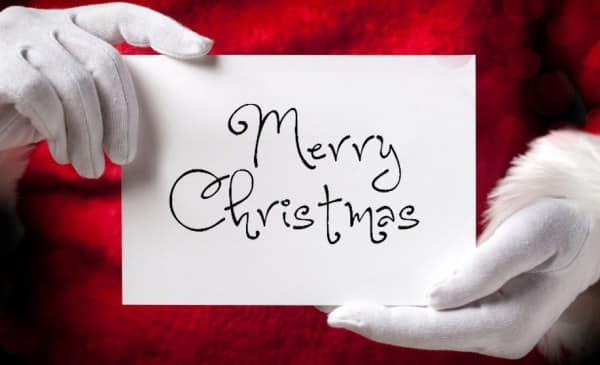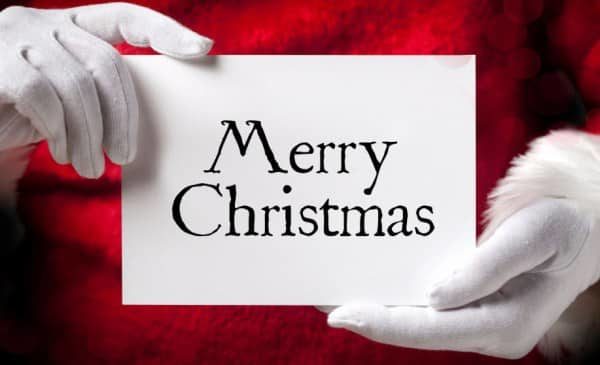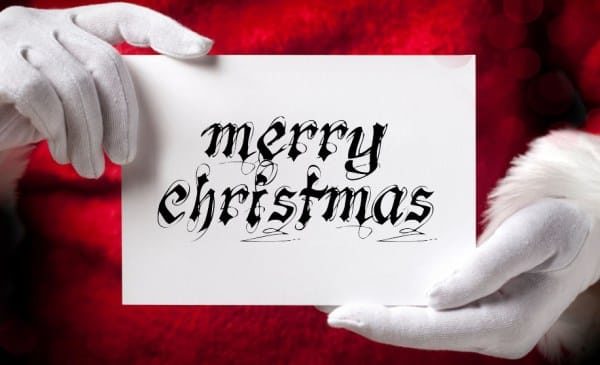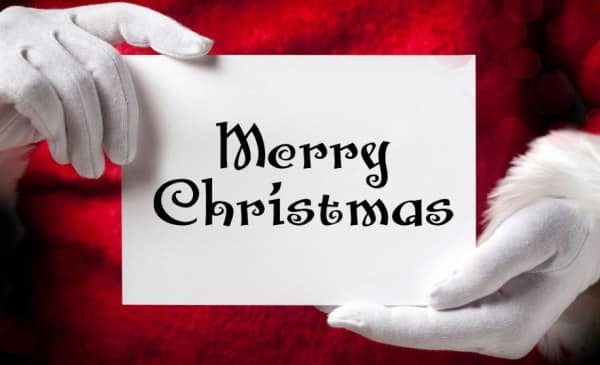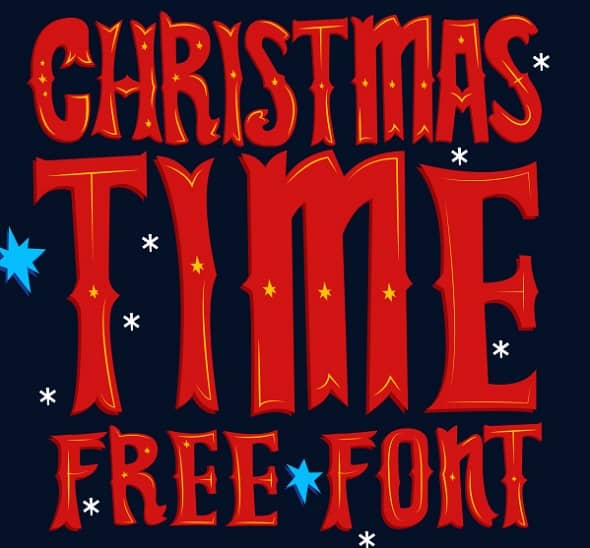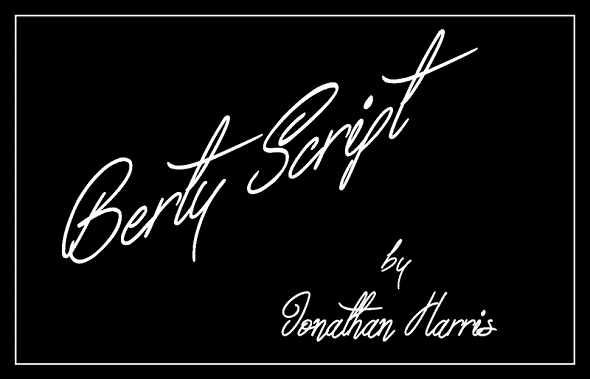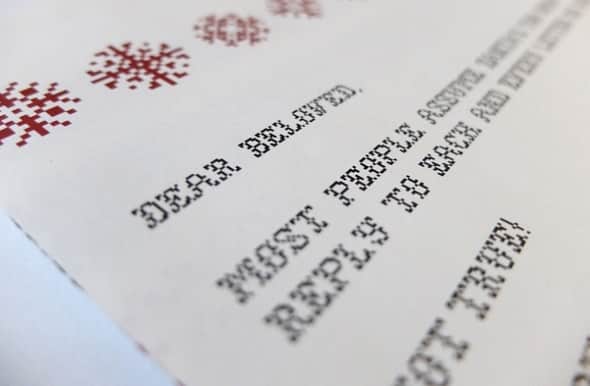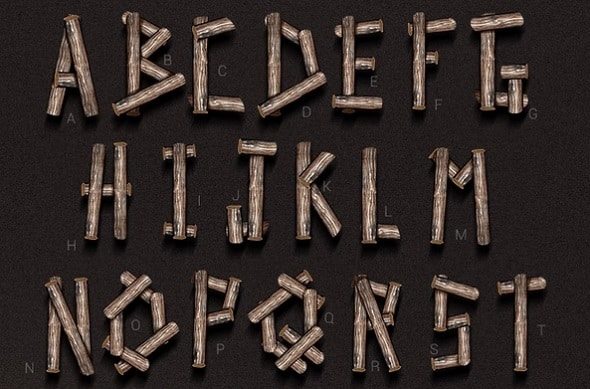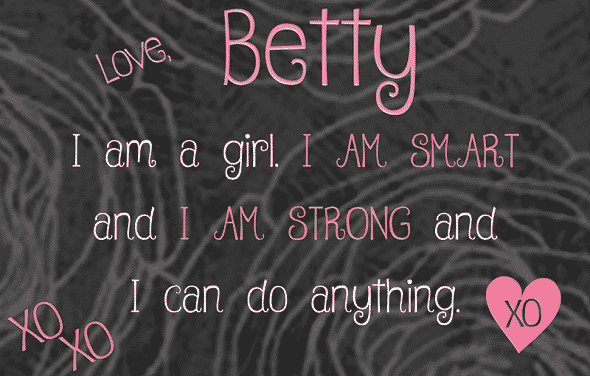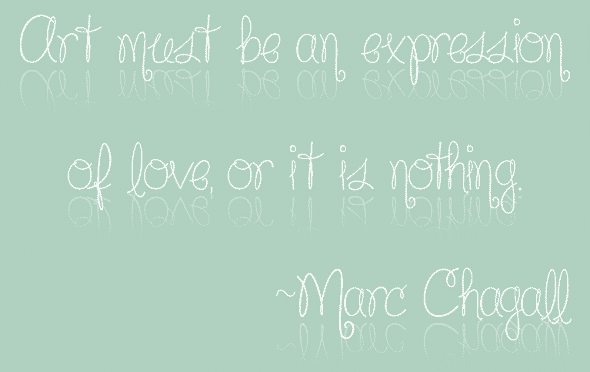
#novemberesource: 70 FONT NATALIZI
Se siete in procinto di realizzare un bel progetto natalizio ecco a voi una collezione di font gratuiti, da usare nei vostri lavori a tema. I font sono liberamente scaricabili mediante il link posto sul titolo e senza vincolo di utilizzo. Ideali per un biglietto di auguri, per una lettera digitale a Babbo Natale o una landing page, sono perfettamente in grado di incarnare quello spirito natalizio di cui necessitate.
Christmas Time Free Font
Festiva – Festive Font
Sunday Free Font
Woody Type Free Font
Christmas Pixel Font
Berty Script Font
CF Jacques Cartier Font
Betty Font
Mougatine Font
DJB Angel Baby
Silver Bellybutton Ring
Icecold Font
PW Christmas Tinsel
Snowinter Font
Dite Alla Giovine Font
Everything Holiday Font
Midnight Hymn Font
DJB Dear St. Nick
Mademoiselle Camille Font
Merry Murni Script 1 Medium
PW Christmas Candies Font
Rebel Pixie Font
Fox in the Snow Font
Goodfish Font
Merry Scriptmas Font
Jollygood Sans Font
FoglihtenNo07 Font
Norse Free Font
Snowinter
Christmas On Crack
Candy Cane
Santa’s Sleigh
Kingthings Christmas
Metro Retro NF
Santa’s Air Mail
PW Christmas Tinsel
Kringle
Xmas TFB Christmas
Christmas Snow
Snow For Santa